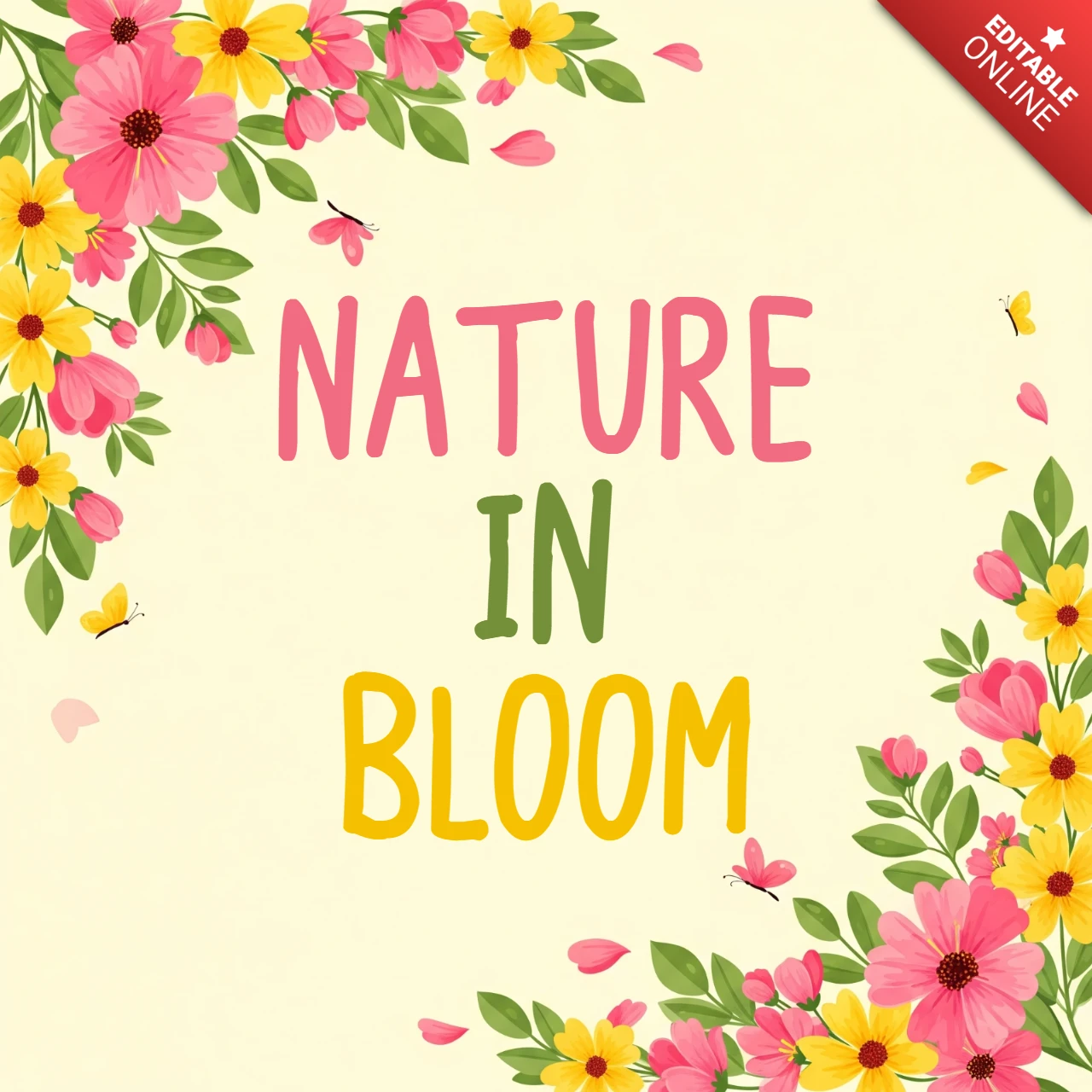
Modèle de design floral printanier pour cartes de vœux avec des fleurs colorées et une typographie fantaisiste
Éditer dans Design Studio Télécharger en JPGÉlevez vos célébrations avec notre modèle de design floral vibrant, parfait pour les cartes de vœux. Avec une typographie fantaisiste et des fleurs colorées, il capture l'essence du printemps et de la nature.